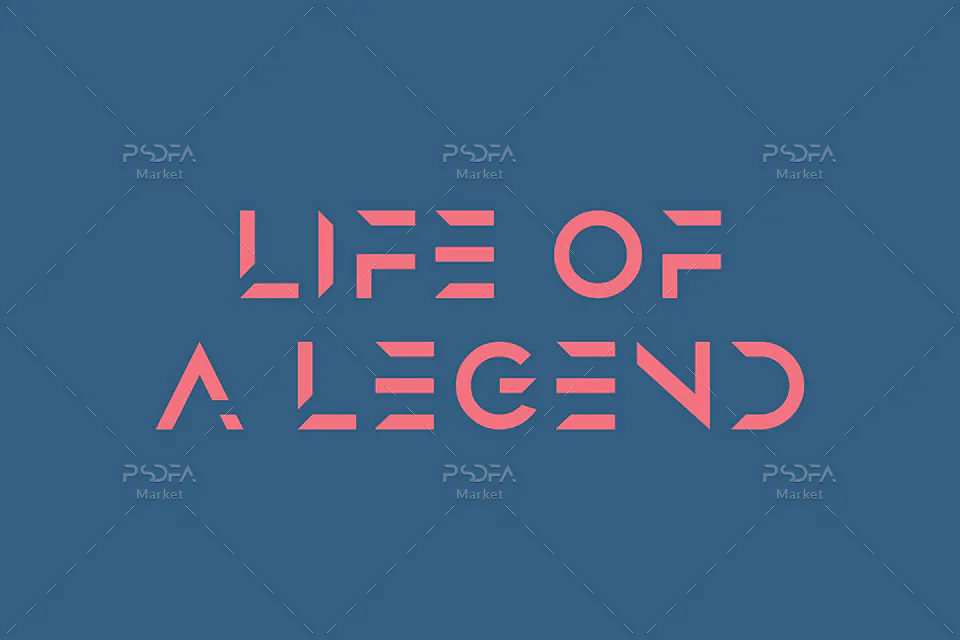
فونت انگلیسی Anurati یکی دیگر از سری فونت های انگلیسی فوق العاده زیبا و جذاب است که می تواند به طرح های گرافیکی شما جذابیت خاصی ببخشد. فونت با پسوند OTF می باشد که دارای حجمی بسیار پایین است. دقت داشته باشید که در استفاده از این فونت Caps Lock کیبورد شما حتما باید روشن باشد یعنی اینکه شما فقط با حروف بزرگ انگلیسی قادرید کلمات خود را در برنامه های مختلف تایپ کنید . پیش نمایش فونت Anurati را می توانید در تصاویر زیر مشاهده کنید.